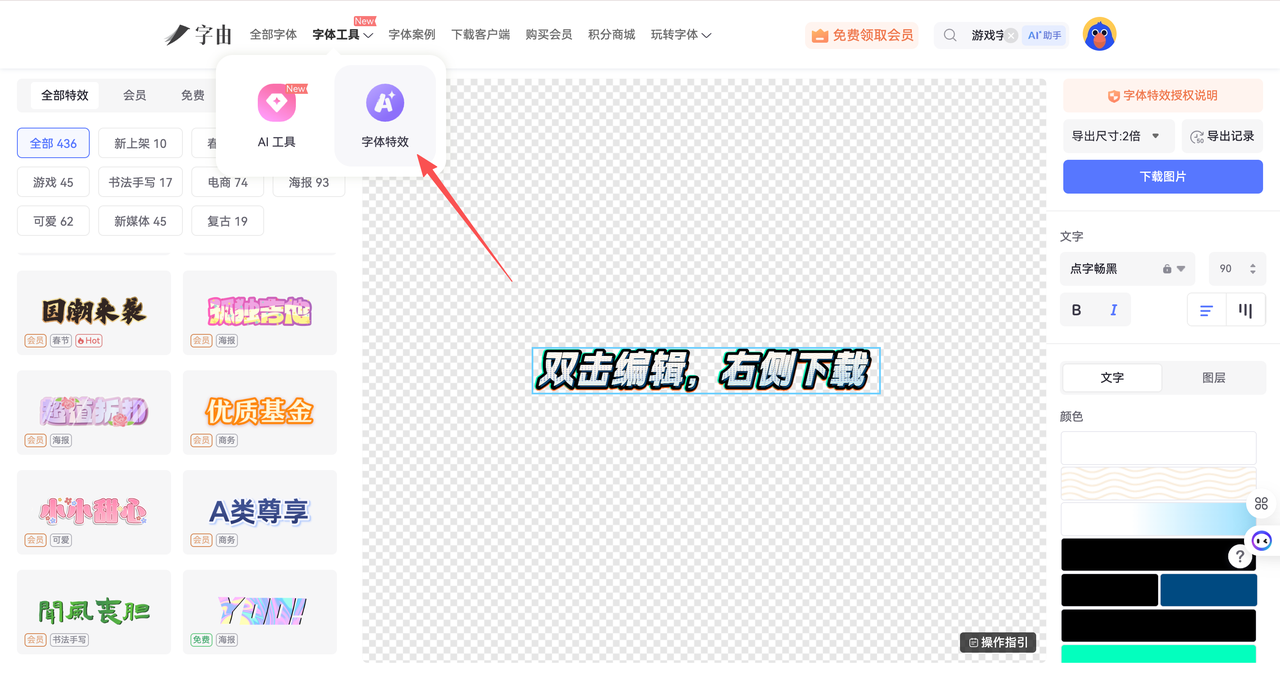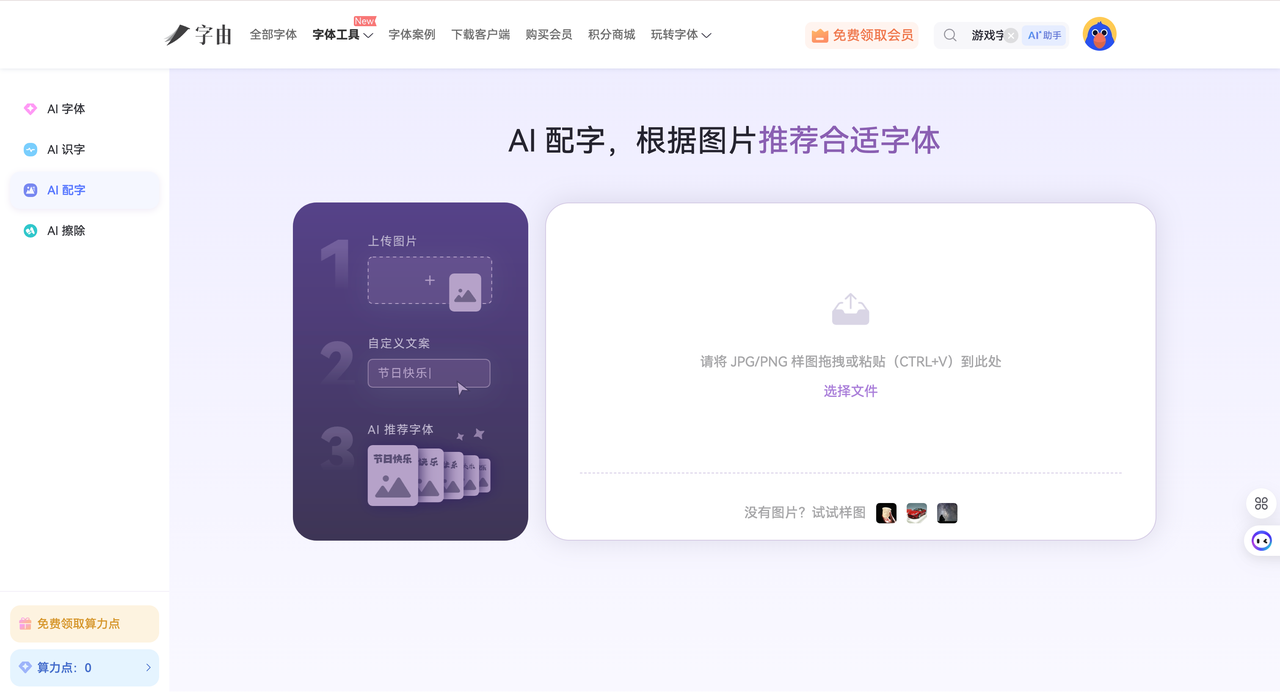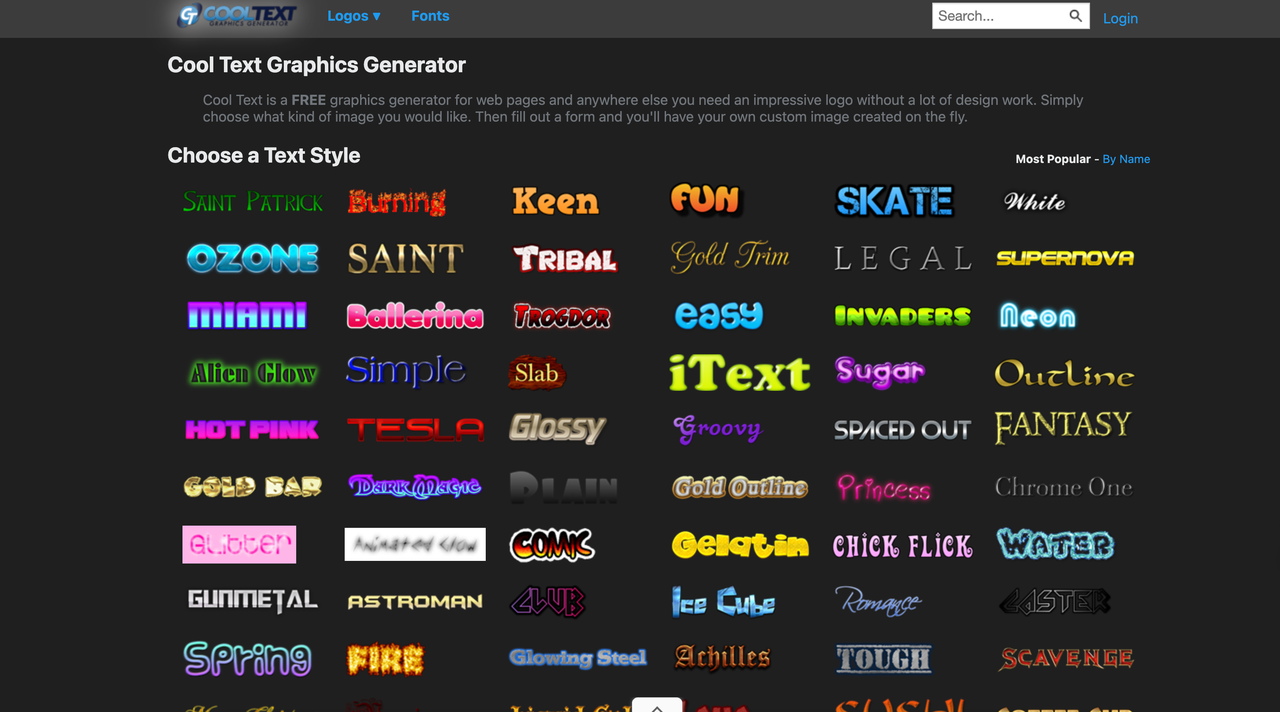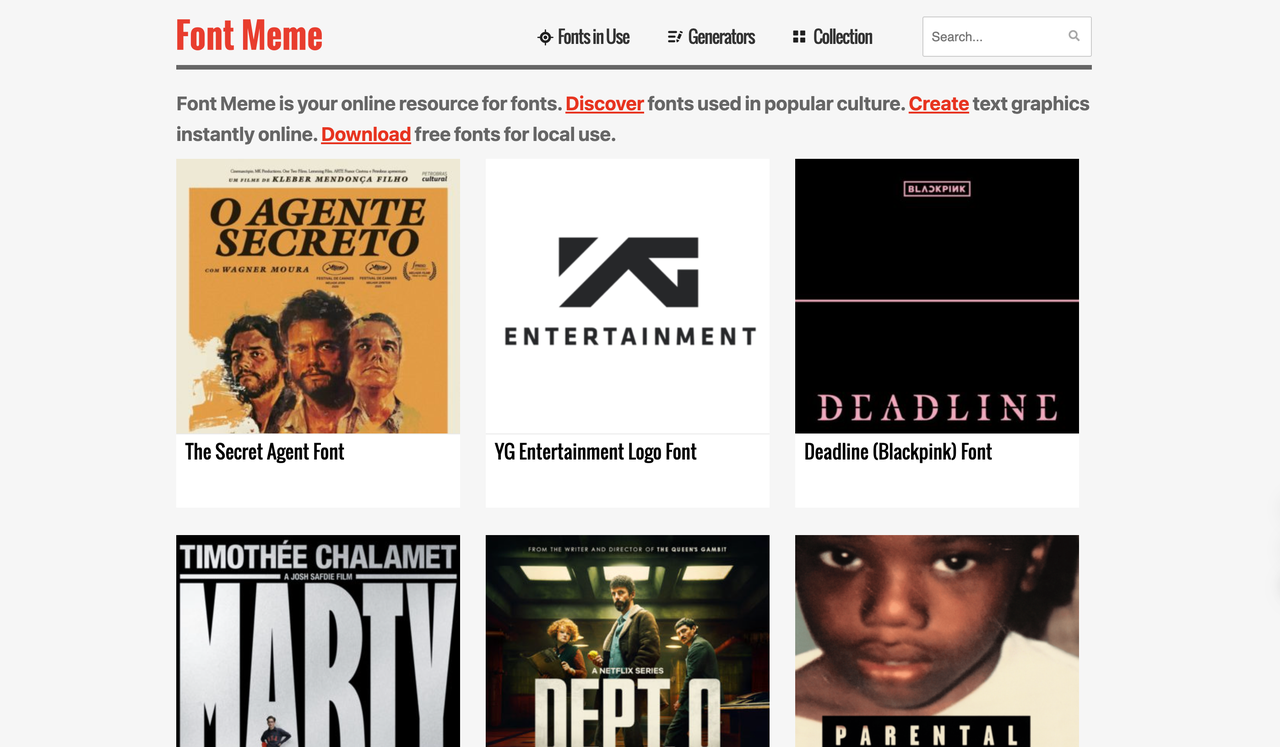
创意字体在线生成器推荐:2026年设计师必备字体工具指南
如果你经常做海报、运营视觉或者品牌设计,大概已经发现一个很明显的变化:标题设计越来越依赖创意字体在线生成器。说实话,我自己最早接触这类工具还是在 2019 年。当时做活动海报,经常要花半小时找字体,下载、安装、重启软件,然后才发现效果不太对。后来逐渐开始尝试各种花体字生成器,效率一下子提升了不少。根据 HubSpot 的营销研究,内容视觉质量会直接影响用户停留时间,视觉设计优化可以让页面停留时间提升 30%以上。一个好看的标题字体,真的能让用户多看你几秒。也正因为如此,越来越多设计师开始使用创意字体在线生成器来快速生成灵感,再结合设计软件进行优化。
如果你本身是设计师,或者经常需要处理字体,我最推荐先试试字由。字由的玩法比普通创意字体转换器更丰富一些。因为普通生成器大多只是把文字转换成 Unicode 花体,而字由更像是一个 “字体生成 + 字体特效 + 字体管理” 的组合工具。目前字由已经拥有 2000 万以上注册用户,很多设计团队都在使用。
如何用字由生成创意字体?
我平时用字由做创意字体设计,一般会用下面这套流程。先打开字由客户端,然后进入字体特效工具。这里其实是一个很多人容易忽略的功能,但设计师用起来非常顺手。字由目前提供 400 多种字体特效模板,覆盖电商、游戏、新媒体、品牌海报等不同场景。
操作过程其实很简单:
• 第一步,在特效编辑页面输入你的文字,比如活动标题或者品牌口号。
• 第二步,选择一个喜欢的字体风格,比如科技感标题、潮流海报字体或者电商促销字体。
• 第三步,可以继续调整颜色、阴影、立体效果以及字距等细节。
通常不到 30 秒,就能生成一个完整的视觉标题效果。
另外一个我很常用的功能是 AI 配字。有时候你已经有一张图片,但不知道应该搭配什么字体。只需要把图片上传到字由,AI会自动识别画面元素,并推荐适合的字体风格,比如:
• 新媒体封面字体
• 品牌标题字体
• 海报装饰字体
这种方式其实也可以理解为一种创意字体在线生成器的智能版本,因为系统会根据图片内容自动给出设计建议。说实话,如果你只是偶尔用花体字生成器做个标题,可能不会觉得差别特别大。但如果你需要频繁做海报、Banner或者社交媒体封面,就会明显感觉到这种工具的效率优势。
2、Cool Text
Cool Text 是一个比较经典的花体字生成器。很多设计师第一次接触字体生成工具,大概率就是从这个网站开始的。我自己也是。那时候做论坛签名图和博客标题,经常用它生成一些简单的标题效果。
使用方法:
Cool Text 的玩法非常简单。进入网站后输入文字,然后从模板里选择一种字体风格,比如3D字体、火焰字体或者金属字体。接下来系统会自动生成一个PNG图片,可以直接下载使用。
优劣势:
非常容易上手,不需要任何设计经验。对于新手来说,这种创意字体转换器能快速帮助你理解不同字体风格。不过如果从专业设计角度来看,它的字体风格稍微有点老。很多模板看起来更像 2015 年前后的网页风格。所以我现在更多是把它当成灵感工具,而不是最终设计工具。
适合人群:
做简单封面图、自媒体标题、论坛头像或者小游戏Logo的人。如果你只是偶尔需要一个花体标题,它依然是一个不错的创意字体在线生成器。
3、Font Meme
Font Meme 和前面的工具有点不一样,它更像一个字体资料库。如果你曾经好奇过电影标题字体是怎么做的,比如《星球大战》《哈利波特》这些经典字体,大概率都能在 Font Meme 里找到类似风格。我之前做一个游戏活动页时,就在这里找到了赛博朋克风格字体灵感。当时先用它生成一个简单标题,然后再在设计软件里重新绘制,这样效率会高很多。
优势:
Font Meme 字体分类特别细。比如电影字体、游戏字体、品牌字体、动漫字体等等。如果你正在寻找2026创意字体灵感,这个网站会非常有帮助。
适合人群:
当然,它本质上还是一个字体生成工具,生成的图片通常需要再进行设计优化。所以更适合有一定设计基础的人使用。
4、创意字体设计的几个经验分享
做设计这些年,我慢慢发现一个挺有意思的现象。很多刚入行的设计师会觉得字体越复杂越好,但其实很多优秀品牌的字体都非常简单。比如苹果官网,大部分标题都是非常普通的无衬线字体。关键不是字体多花,而是排版和比例。这里分享几个我自己经常用的技巧:
• 第一,尽量不要在一个页面使用超过两种字体。字体太多会让视觉非常混乱,这是很多新手容易犯的错误。
• 第二,字体一定要匹配品牌情绪。科技品牌通常适合干净的无衬线字体,而复古品牌更适合衬线字体或者手写风格。
• 第三,别忽略字距。很多海报看起来不高级,其实问题并不是字体,而是字距太紧。我通常会把标题字距增加 10% 到 20%,整体观感会明显提升。
根据 Adobe Creative Trends 报告,AI辅助设计正在成为主流创作方式,越来越多设计师会先使用生成工具寻找灵感,再进行手动优化。这也是为什么创意字体在线生成器在2026年越来越常见。